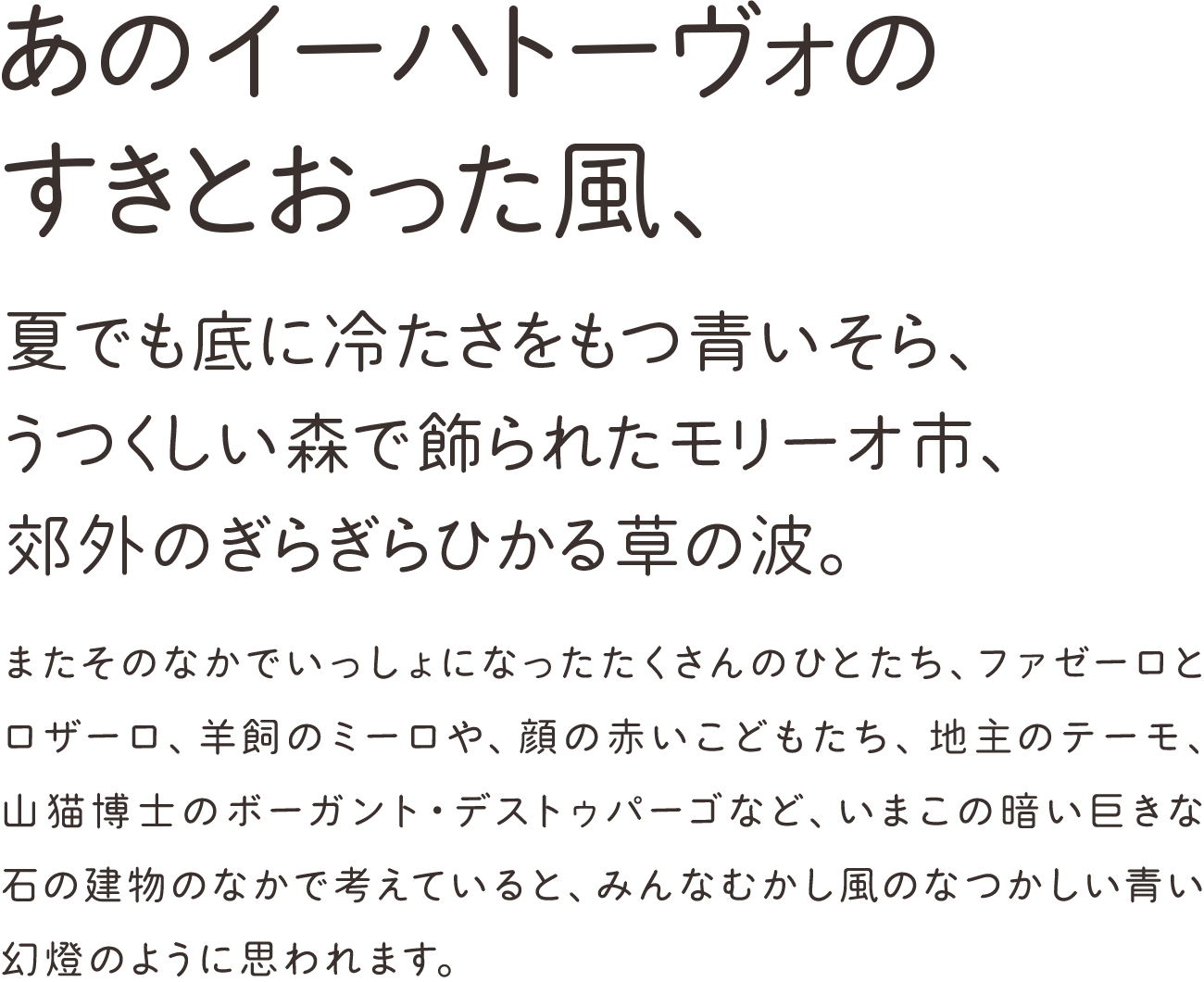
丸丸ゴシックBSr
3種類のかなと2種類の角丸で使い分けができる、やさしくてかわいい丸ゴシック体フォント。「A」は明るい印象で、「B」はクセが少なく、「C」は落ち着きのあるデザイン。漢字は共通で、小さめカーブの「Sr」とゆったりカーブの「Lr」が用意されています。
※かなのデザインが違う3種類のシリーズ。漢字はカーブの小さいSrと大きいLrが用意されています。